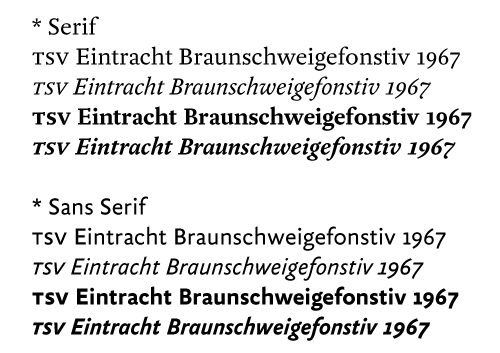
Ich bräuchte gute Tipps von erfahrenen Typografen
endlich bin ich (finanziell) so weit mir eine Schrift zuzulegen und plötzlich merke ich, dass mir die Entscheidungsfähigkeit fehlt. Gesucht wird von mir eine serifenlose, klare, schöne (ist relativ, ich weiss), seriöse Schriftfamilie, die flexibel einsetzbar ist, nicht zu modisch, nicht verspielt, selbstverständlich gut lesbar, ausgeben kann ich ca. 1000 Dollar, keine Kapitälchen sind notwendig.
Ich habe auf myfont die "bestsellers" angeschaut, Helvetica Neue (nicht ganze) und Interstate sind auch unter meinen "top ten", trotzdem bin ich sehr unsicher, ich will das Geld gut investieren.
Ich möchte euch um konstruktive Tipps bitten, ich habe mich in den letzten Tagen durch viele Foundries durchgekämpft, viel Schönes gesehen, was mir allerdings die Sicht nur noch verdunkelt hat, ich muss scheinbar zurück zu dem Ursprung.
Die Unit-Familie könnte dir gefallen. Möchtest du alle zukünftigen Aufgaben mit nur einer Schrift bewältigen? Für 1000 € kannst du doch mehrere Familien ansehen und dann eine Mischung machen.
Irgendwie doch ein komisches Ansinnen. Ich käme mir als Ratgeber merkwürdig vor, etwas zu empfehlen, ohne zu wissen, wofür. :?
Wenn mir jemand sagen würde, dass er sich selbstständig machen will und ich soll ihm sagen, welches Werkzeug er dazu braucht, würde ich zuerst zurückfragen, ob er eine KfZ-Werkstatt eröffnen will, einen Malerbetrieb oder eine Computerfirma...
Ist es in der Typografie nicht mehr so, dass man sich an seinem Auftrag/Auftraggeber orientiert?
Ich vermute mal dass Agnes einen Font für sich selbst sucht. Da sie "optische Gestaltung" angibt und die potentiellen Kunden aus allen möglichen Himmelsrichtungen kommen können, würde ich ihr die HelveticaNeue, die Frutiger oder – wenn’s schmäler sein soll – die Conduit empfehlen. Weil ich die einfach toll und höchst universell einsetzbar finde.
National von Kris Sowersby sitzt bisschen zwischen steif/streng/sachlich und freundlich/individuell/gutlesbar. Gut ausgebaut und trotzdem nicht teuer (kleines Paket schon für $150)
das klingt eher nach dem wunsch für eine grundausstattung an fonts, oder? (weil du ja nicht sagst für welchen job). schau dir mal verschiedene packages an bei fontshop oder auch bei den schriftenhäusern selber.
Gute, schöne und lesbare Serifenlosen gibt es heutzutage viele.
Als Buchgestalter arbeite ich gerne mit FF Kievit (FontShop) und LF TheSans (Lucasfonts.com) , die beide besser als Textschrift geeignet sind als zB (Neue) Helvetica oder Interstate.
Bei MyFonts.de sind wir begeistert von der neuen Secca von Andreas Seidel. Ein großes Vorteil ist, dass man zum Testen die beiden Grundschnitte Secca Regular und Bold kostenlos als Demoversion herunterladen kann. Mehr Info und Bilder findest Du hier:
Wenn Du etwas suchst, das aussergewöhnlicher aussieht, dann gibt es zB die Museo von Jos Buivenga (MyFonts.com), die sehr geometrisch wirkt aber auch sehr lesbar ist. Auch hier wiederum zwei Gratis-Schnitte.
Ich meine es genau wie das Bertel beschreibt. Ich habe dabei kein konkretes Ziel (merke aber bei den laufenden Projekten, dass mir an einer guten Auswahl fehlt), möchte einfach gute Schriften FÜR MICH bei der Hand haben, die können ruhig teuer sein, aber für den Preis erwarte ich, dass ich sie oft, und zu verschiedenen Themen einsetzen kann. Momentan kann ich mir solche Investition leisten.
Wenn bei einem Projekt der Kunde eine spezielle Schrift haben will, wird sie von ihm gekauft, ich könnte mir doch unmöglich leisten zu jedem Projekt eine teure Schrift aus eigener Tasche zu bezahlen.
Danke für eure Hinweise, ich werde mir jetzt Zeit für eure Tipps nehmen, die Schriften anschauen. Ich werde auch in den nächsten Tagen hier reinschauen.
@ ChristianBüning: eine Mischung klingt interessant, wie mache ich so etwas? Bei der gesuchten Schrift bin ich darauf gekommen, dass ich ca. 8-10 Schnitte brauche + "italics", da komme ich bereits preislich auf die ca. 1000 Dollar... Ich habe auch eine CD von Bitstream gesehen (um 500 Euro), es gibt dort viele Schriften, aber die sind meistens altmodisch, oder unseriös, hm, ich kann mir nicht vorstellen einen guten Kunden damit beeindruckt zu haben.
Die Unit-Familie könnte dir gefallen..
Diese Schrift ist sehr schön, allerdings die große "I/i" Buchstabe irritiert, besonders wenn sie öfter in einem Satz vorkommt.
Taz III ist ein wenig zu schmal, was bei den längeren Texten erst richtig auffallen wird.
Momentan neige ich am stärksten zu Kievit.
Danke für Eure sehr guten Tipps.
Und darf ich fragen welche Schriftart von euch "überall" verwendet wird?
Falls du Windows Vista nicht hast - bei Microsoft kann man ein PowerPoint-Update runterladen, da sind wirklich tolle Schriften dabei - für gratis! Auch wenn Du Ein Adobe Produkt besitzt, sind da meist schon einige gute Schriften wie die Myriad und die Minion dabei.
Es wurden schon sehr gute Vorschläge gemacht. Vielleicht ist hier oder hier auch noch was dabei. Wenn du noch bis Dezember warten kannst, könnte dir die nachfolgende [bald erscheinende] Familie gefallen. :huhu: